영상을 제작할 때마다 요즘 어떤 폰트를 많이 사용하는지 검색하게 되는데, 매번 검색할 때마다 나오는 폰트들이 계속 똑같은데 필요할 때마다 검색하는 제 자신이 싫어서 정리하게 되었습니다. 이번 글에서는 고딕 폰트들 7개를 소개드릴 예정이고, 앞으로 명조편, 강조 자막편, 손글씨편을 정리할 예정입니다. 상업적 무료 이용이 가능한 7개 고딕 폰트들을 알아보도록 하겠습니다.
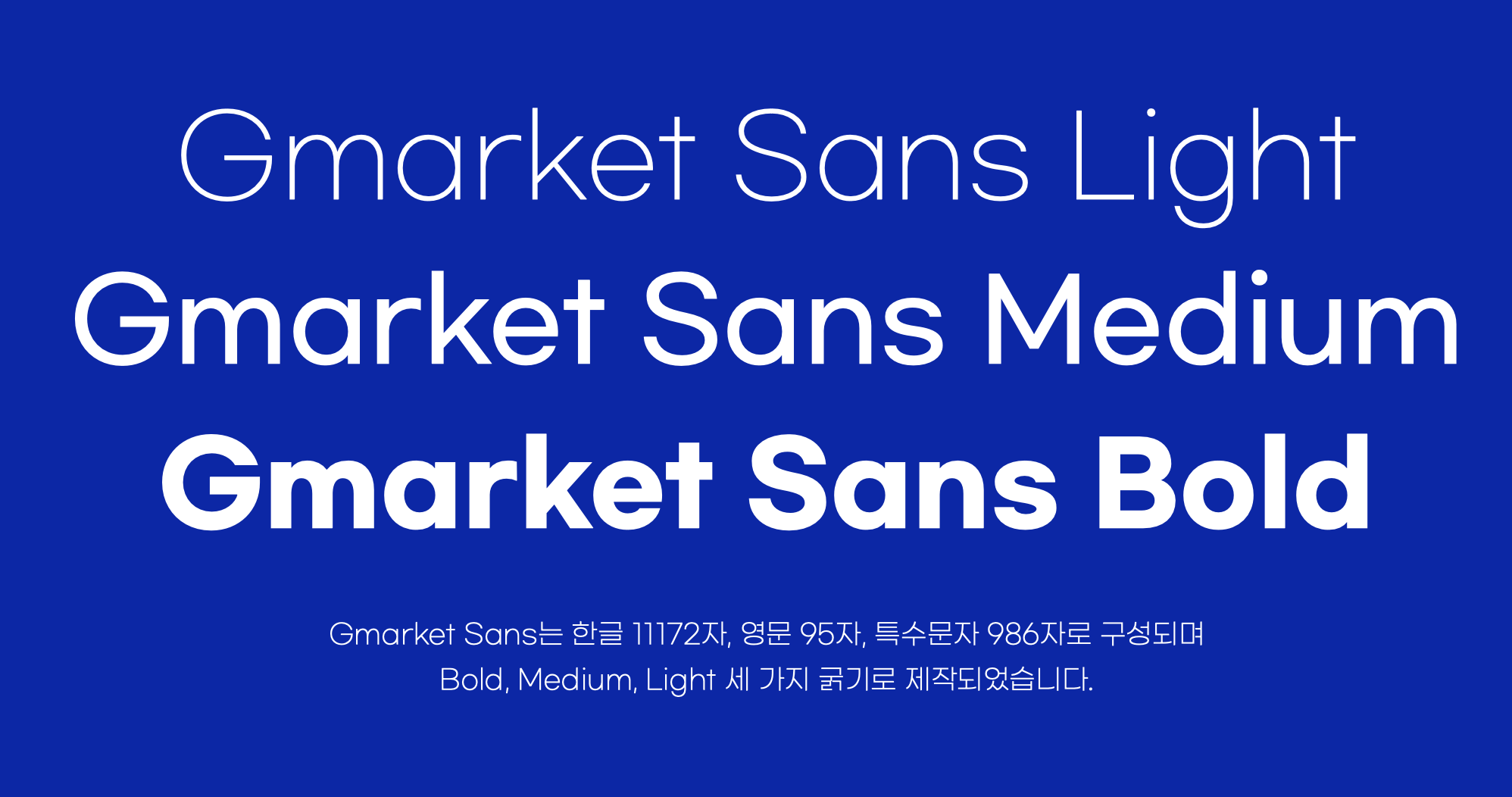
1. 지마켓 산스 (Gmarket Sans)
지마켓에서 제공하는 지마켓 산스는 깔끔하고 정돈된 고딕체입니다. 다양한 굵기를 제공하여 웹디자인, 포스터, 프레젠테이션 등 다양한 디자인에 활용되고 있습니다. 얇은 서체에서 굵은 서체까지 다양한 굵기를 지원하기 때문에 텍스트 강조와 가독성을 모두 잡을 수 있는 폰트라고 생각합니다.
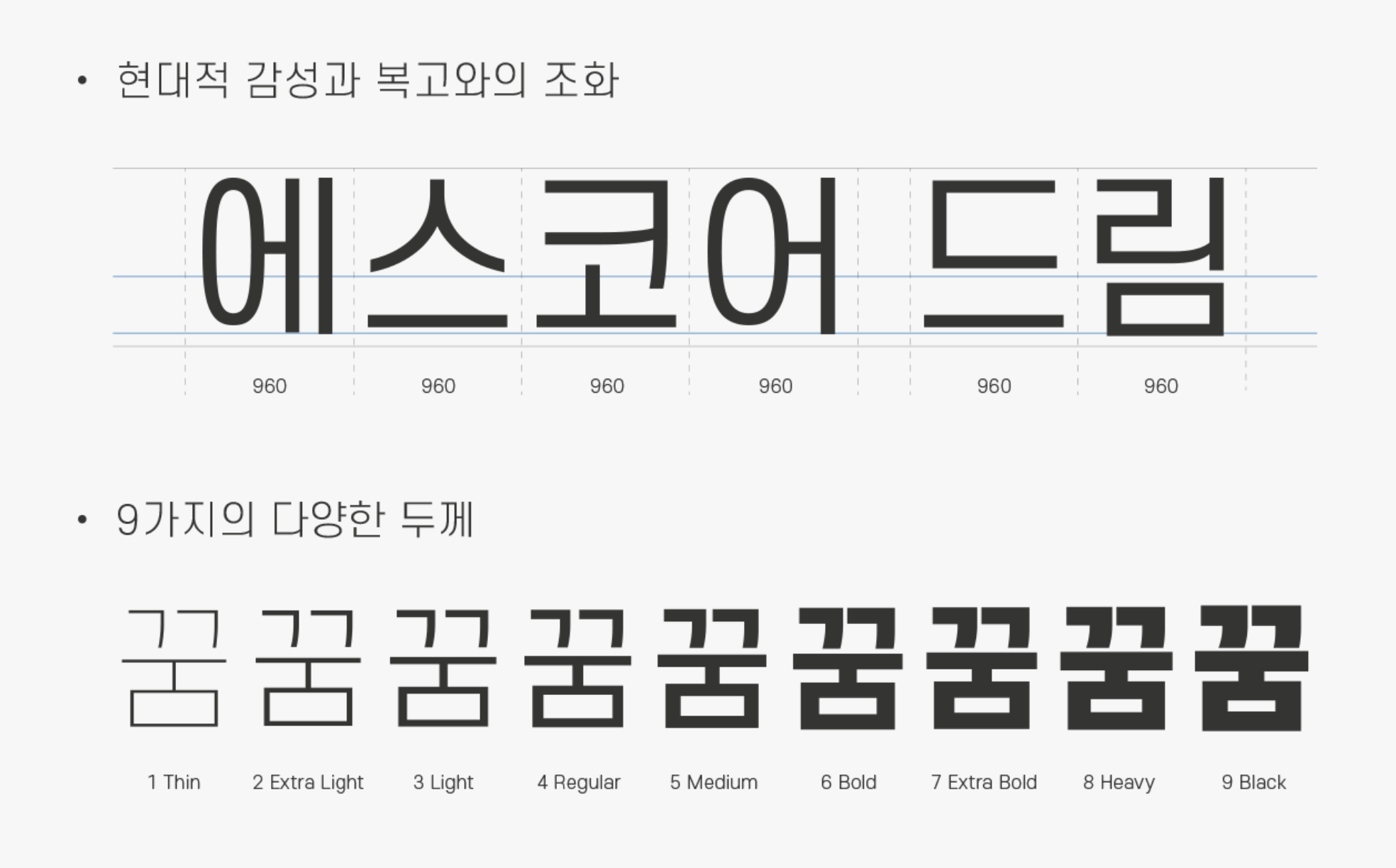
2. 에스코어 드림 (S-Core Dream)
네이버와 함께 개발된 에스코어 드림은 안정적인 글자 구조와 다양한 굵기로 본문, 제목, UI 디자인 등 모든 용도에 적합한 고딕 폰트입니다. 가독성이 뛰어나다고 생각하고, 깔끔하고 모던한 디자인 덕분에 예전부터 오랫동안 이용되고 있는 폰트입니다.
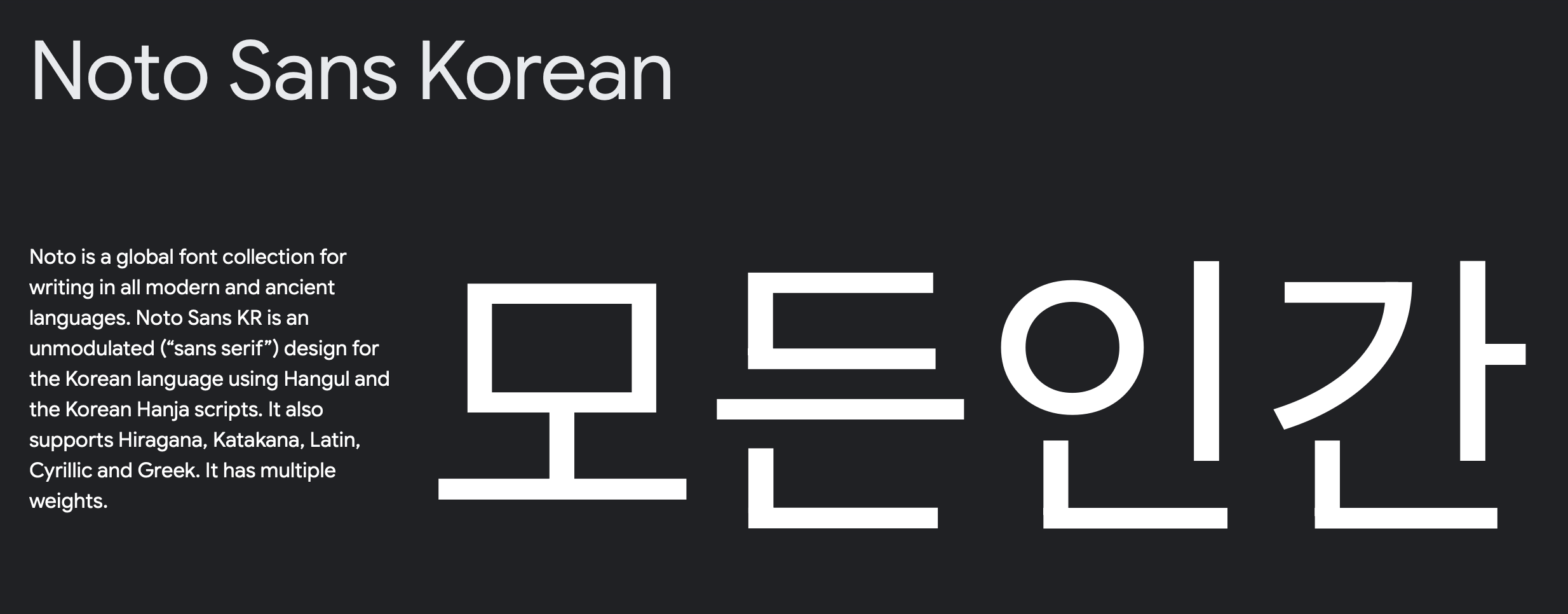
3. 본고딕 (Noto Sans KR)
구글과 어도비가 공동으로 개발한 본고딕 (Noto Sans KR)은 다국어 지원을 위해 제작된 글로벌 폰트라고 합니다. 한국어를 포함한 다양한 언어를 일관된 스타일로 표현할 수 있으며, 간결하고 현대적인 고딕체로 평가됩니다. 웹디자인이나 모바일 앱 UI 디자인에 특히 적합하다는 평가입니다.
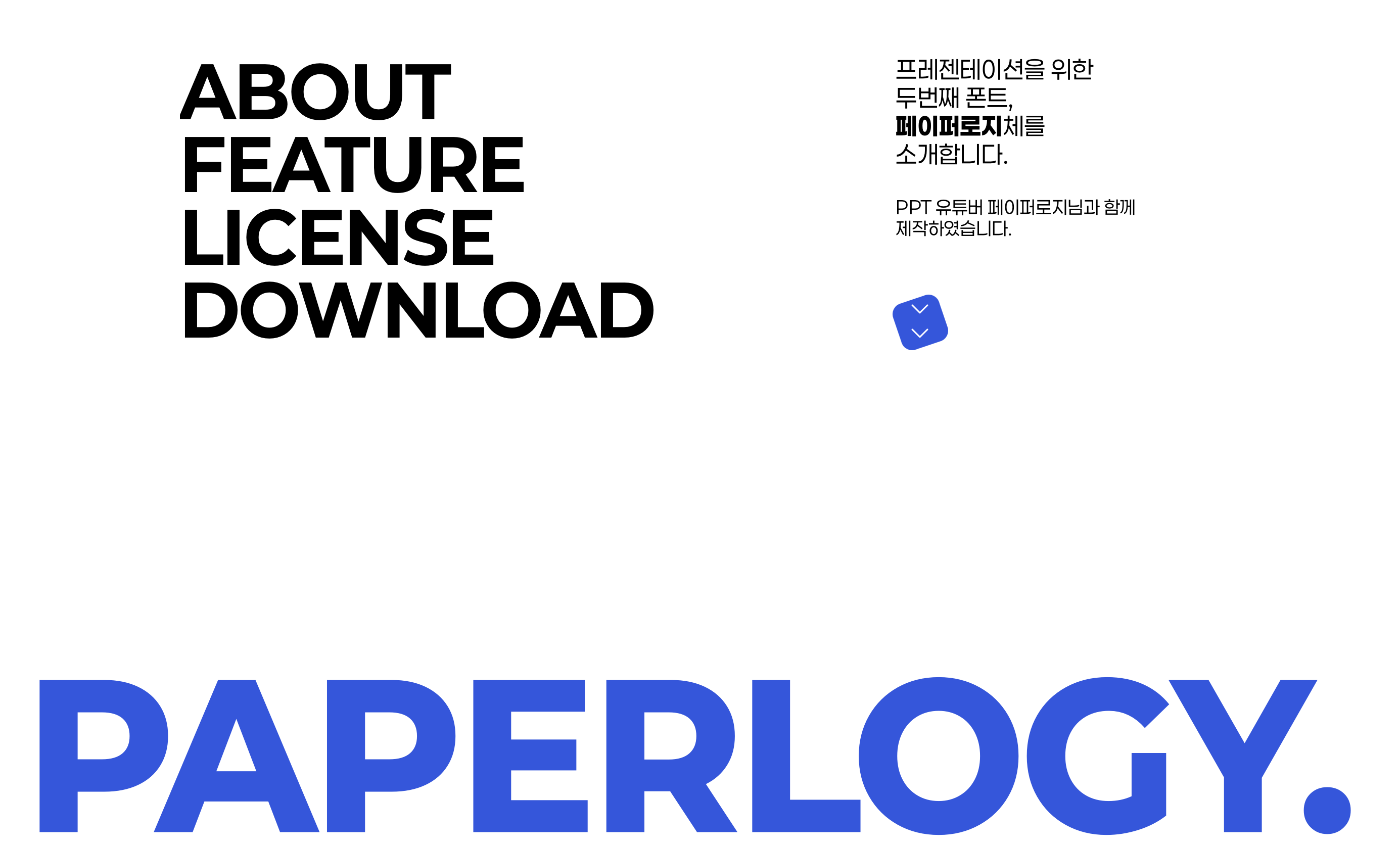
4. 페이퍼로지 (Paperoji)
저는 요즘 이 폰트를 가장 많이 이용하는 것 같습니다. 페이퍼로지는 독특한 감성의 고딕 폰트로, 기존의 고딕체와는 조금 다른 개성 있는 스타일을 자랑합니다. 굵은 서체이기 때문에 제목이나 포스터 디자인에서 사용하면 좋을 것 같습니다.
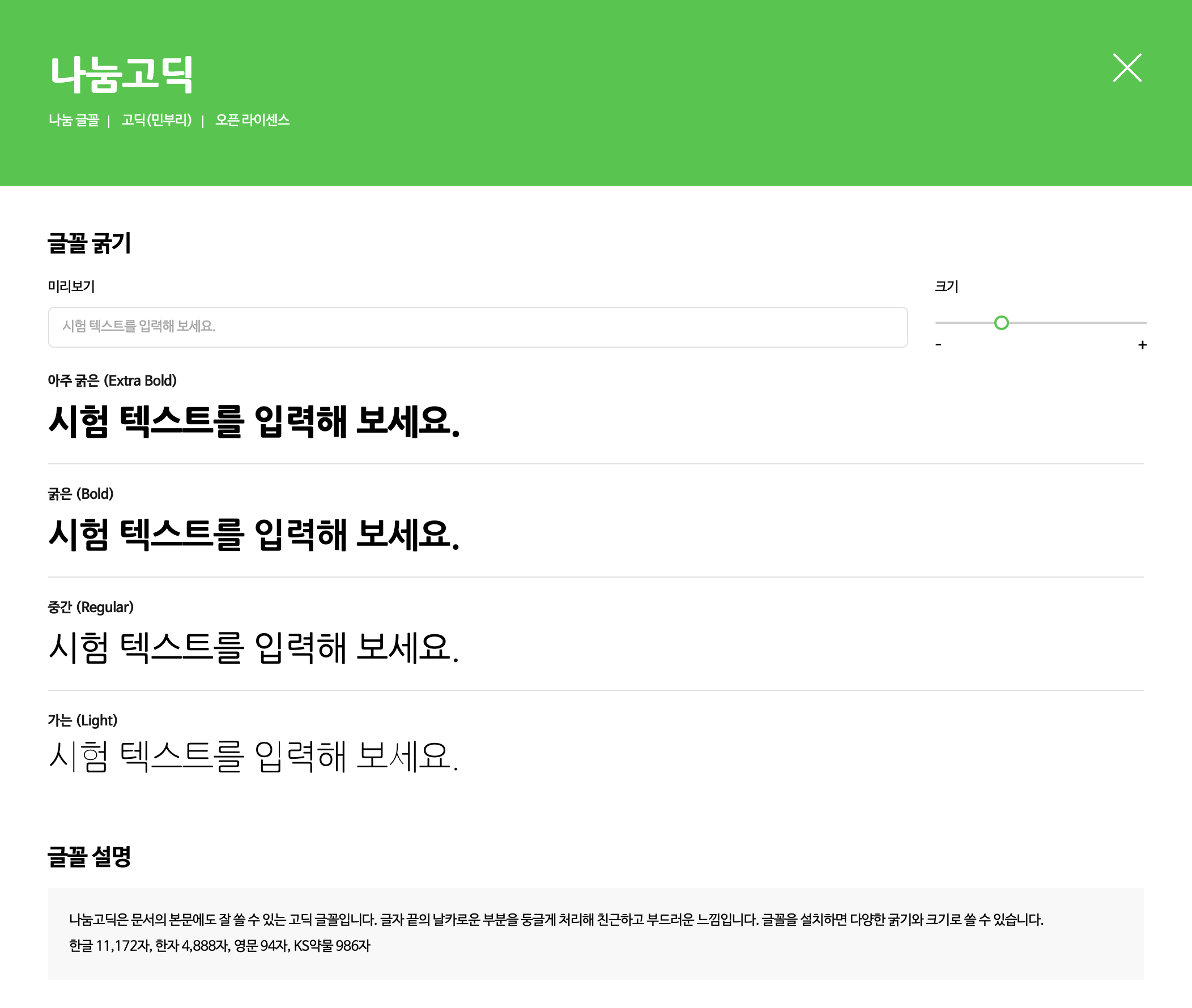
5. 나눔고딕
네이버에서 제공하고 있는 나눔고딕은 가장 널리 사용되고 유명한 고딕체 중 하나입니다. 다양한 굵기를 지원하는 것은 물론 어디에나 어울리는 높은 가독성을 가진 폰트입니다.
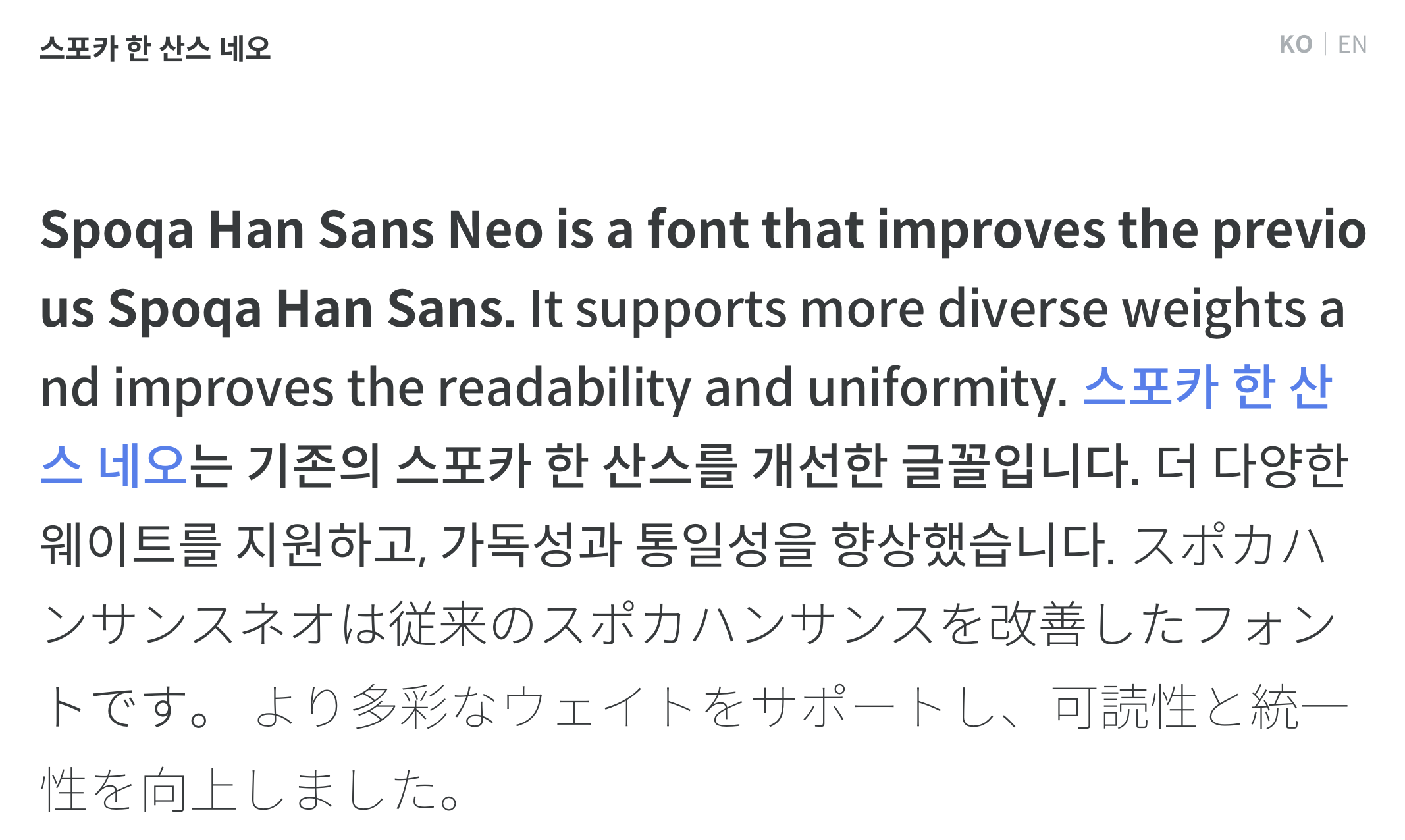
6. 스포카 한 산스 (Spoqa Han Sans)
스포카 한 산스는 간결하고 깔끔한 고딕 스타일이 특징인 것 같습니다. 웹사이트와 앱 디자인에 널리 사용되며, 본문과 제목 모두에서 가독성을 유지할 수 있도록 다양한 굵기를 지원하고 있습니다.
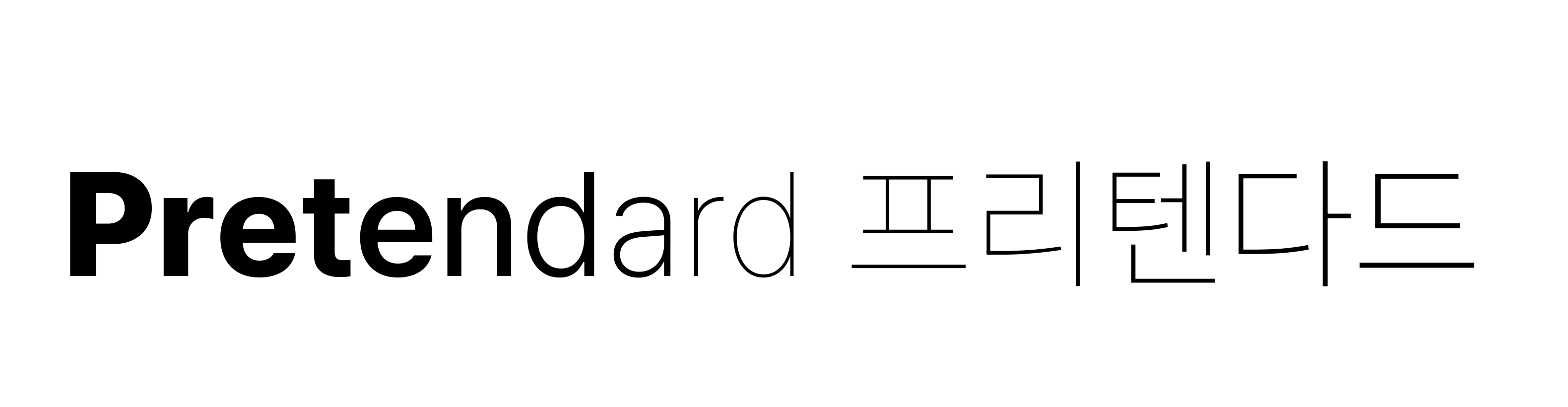
7. Pretendard
Pretendard는 모던한 고딕 폰트입니다. 다양한 굵기와 스타일을 제공하며, 모든 플랫폼에서 가독성과 디자인적 완성도를 높일 수 있는 폰트라고 생각합니다.